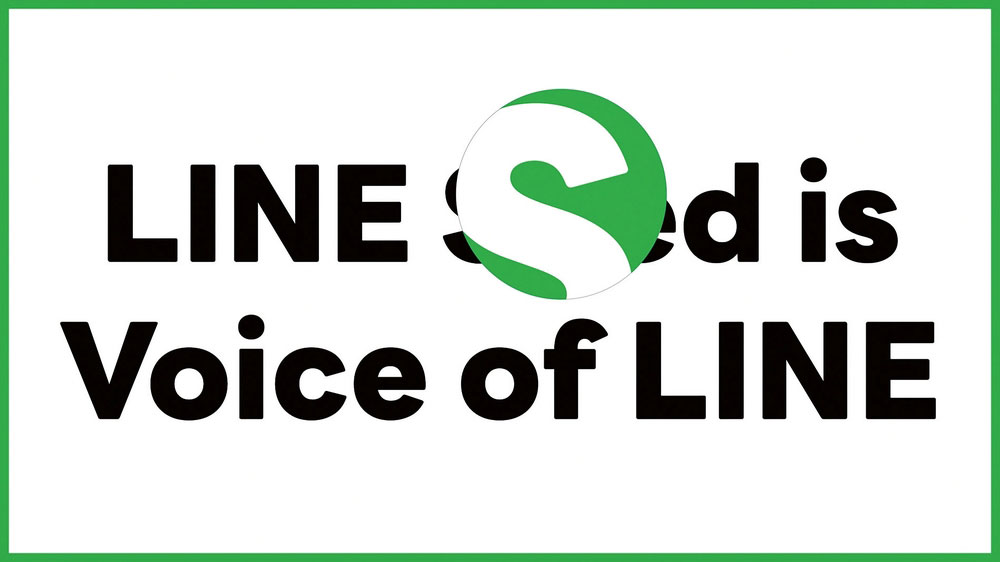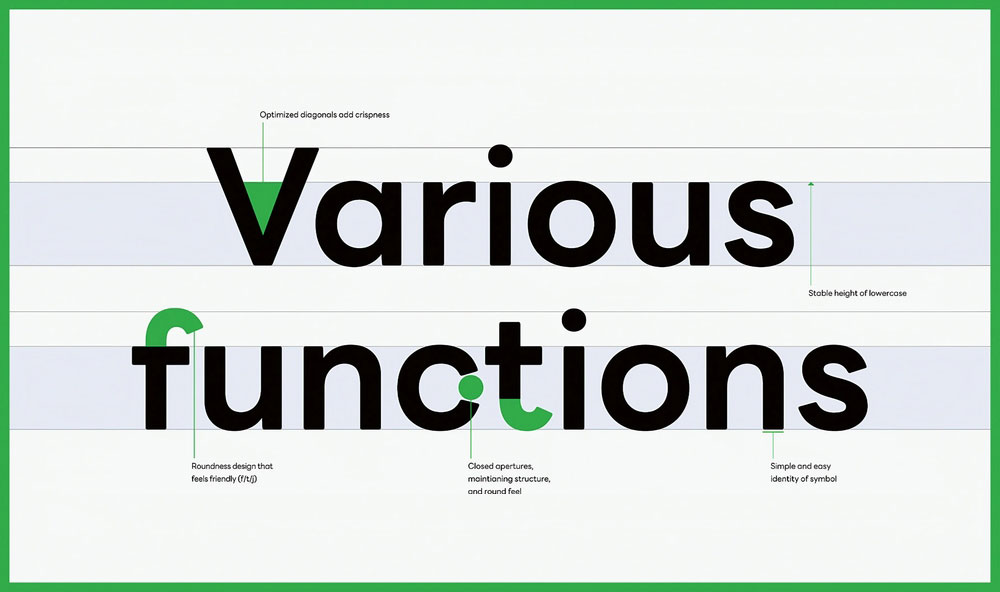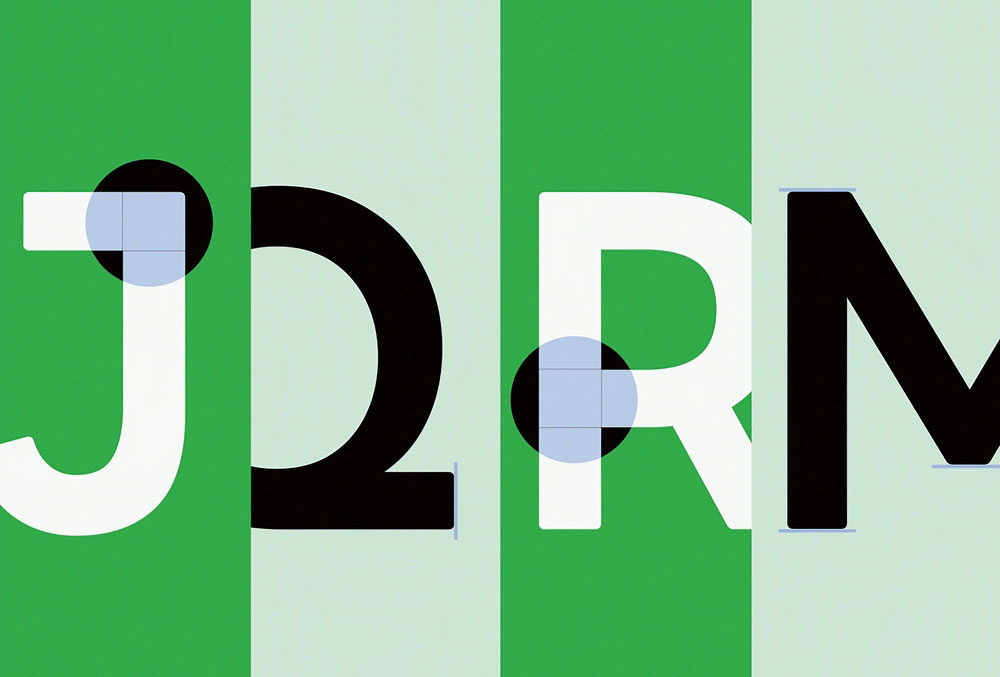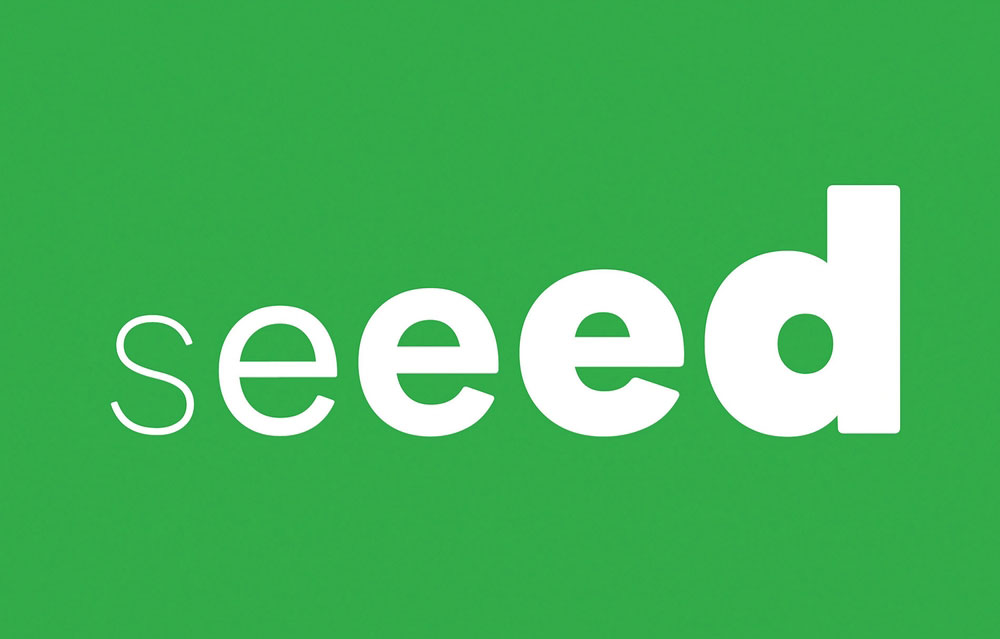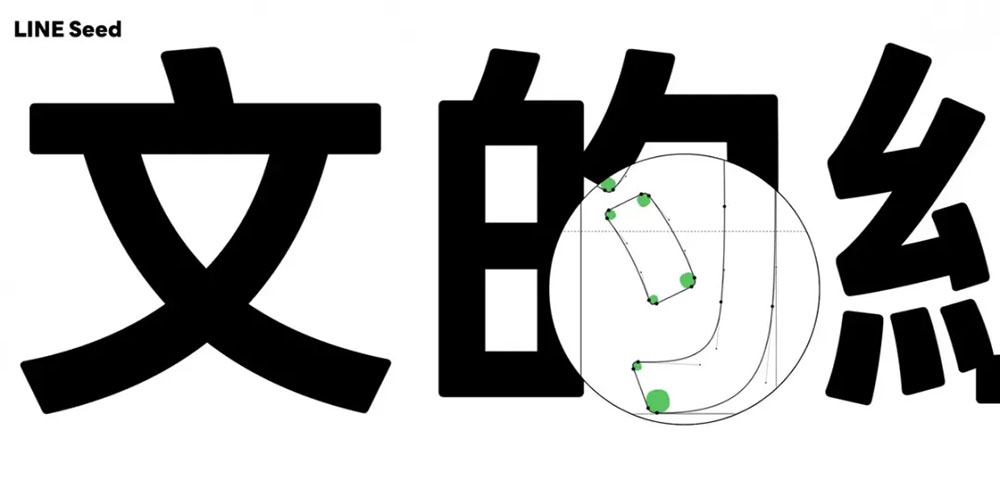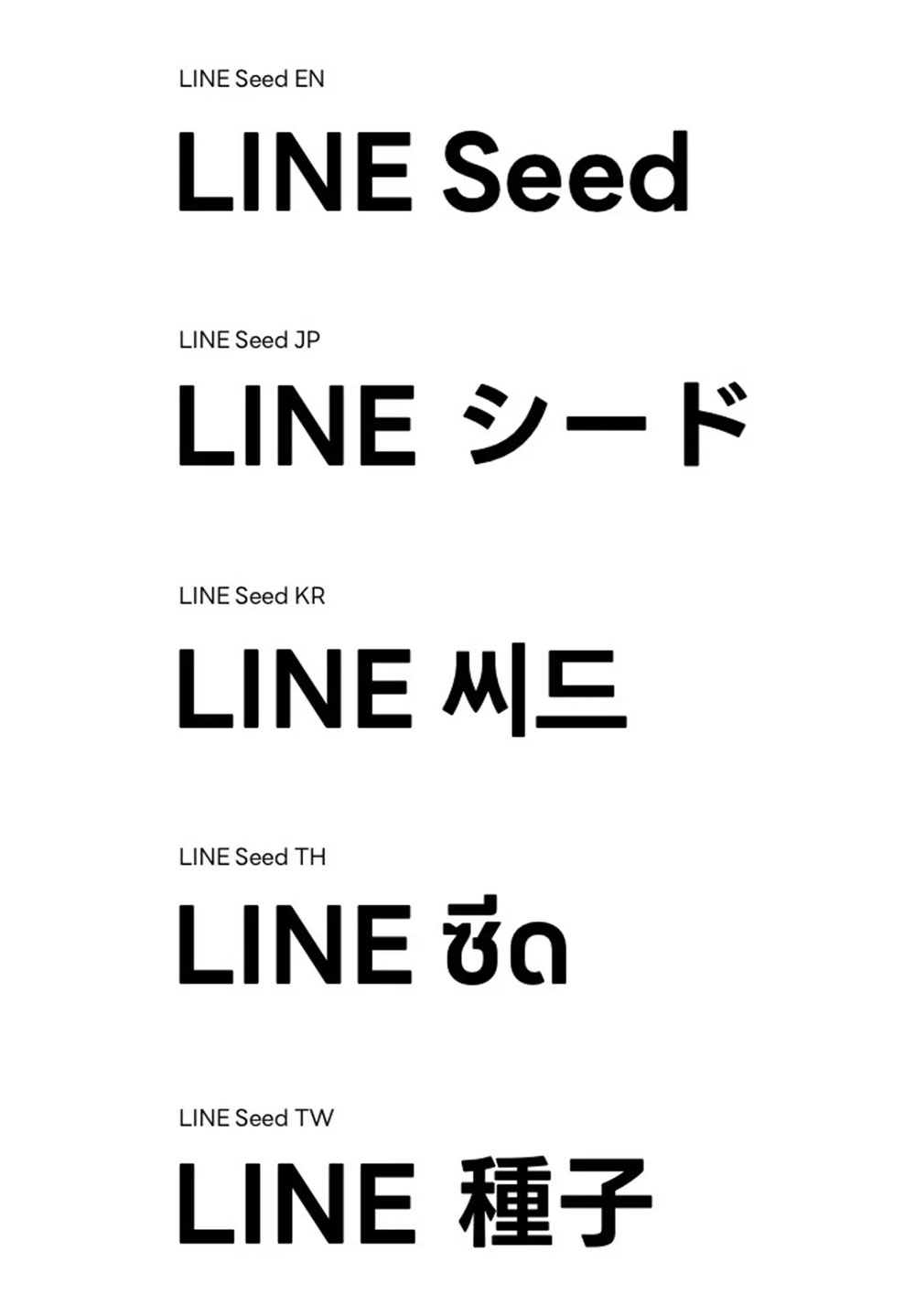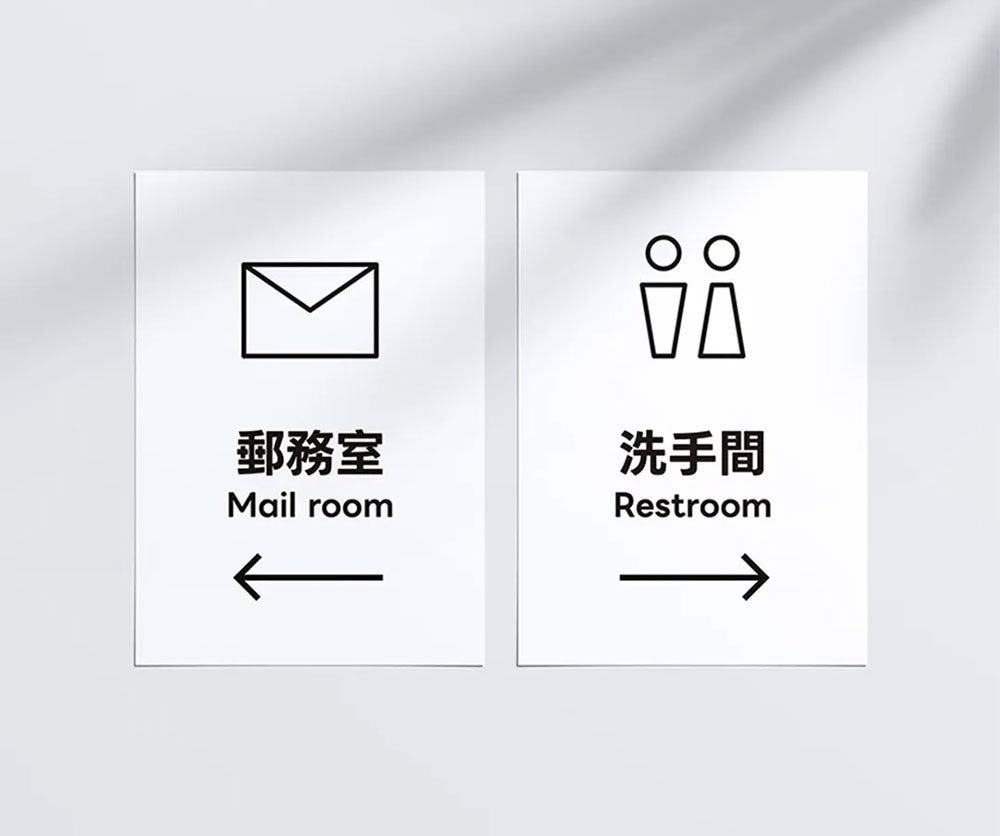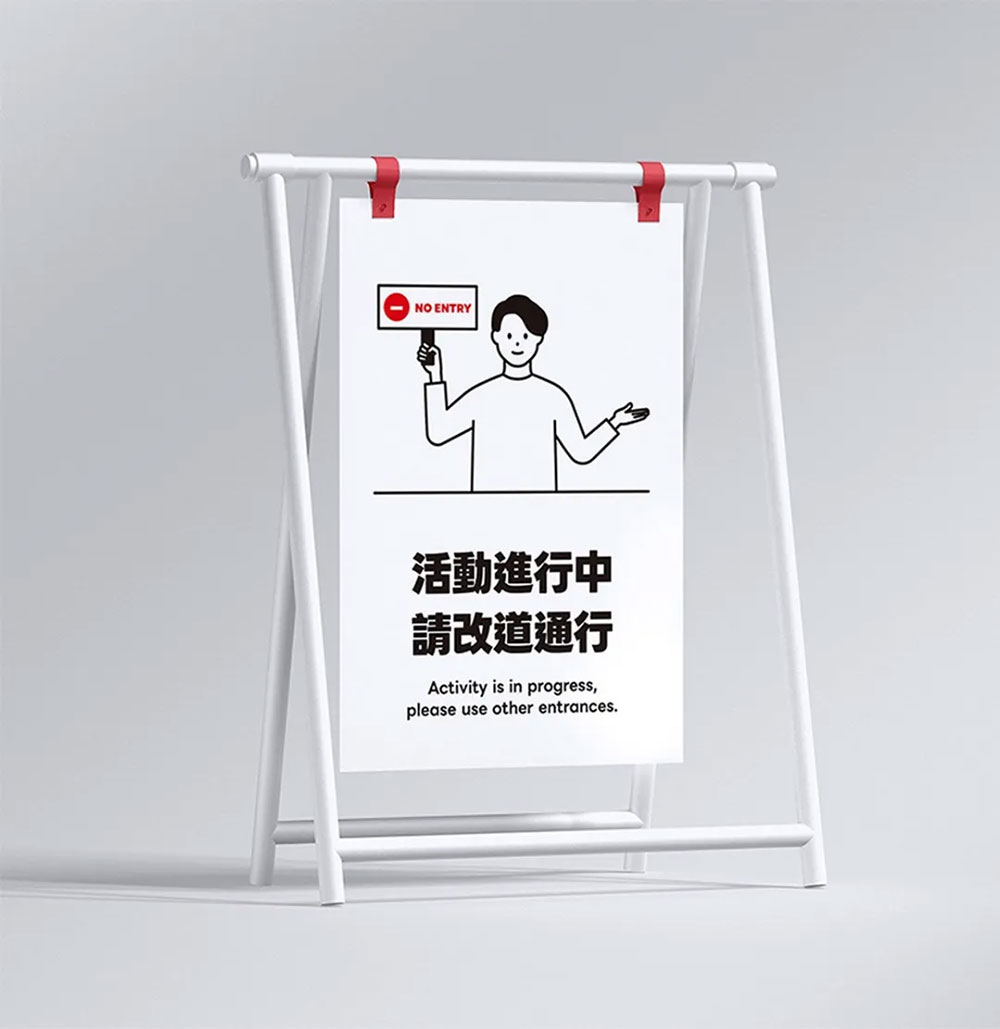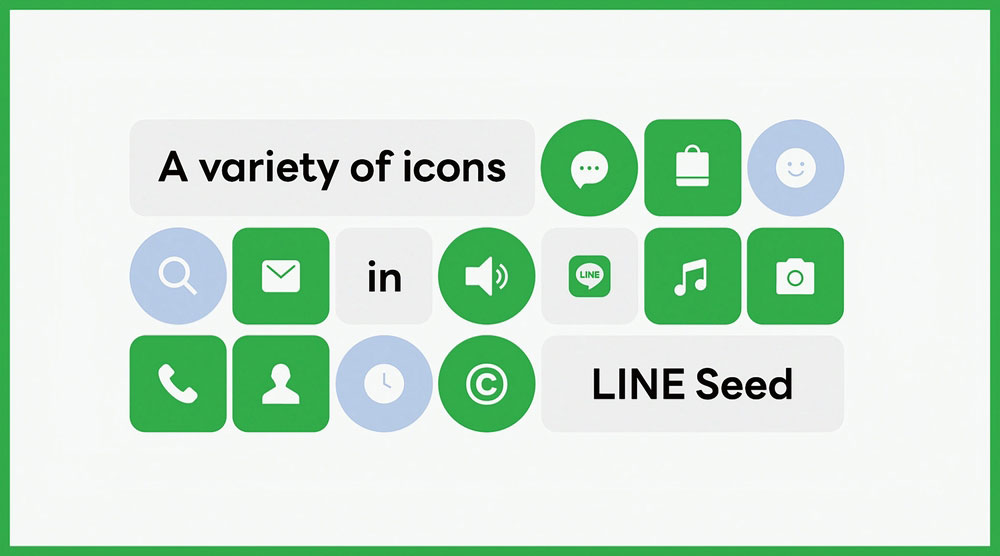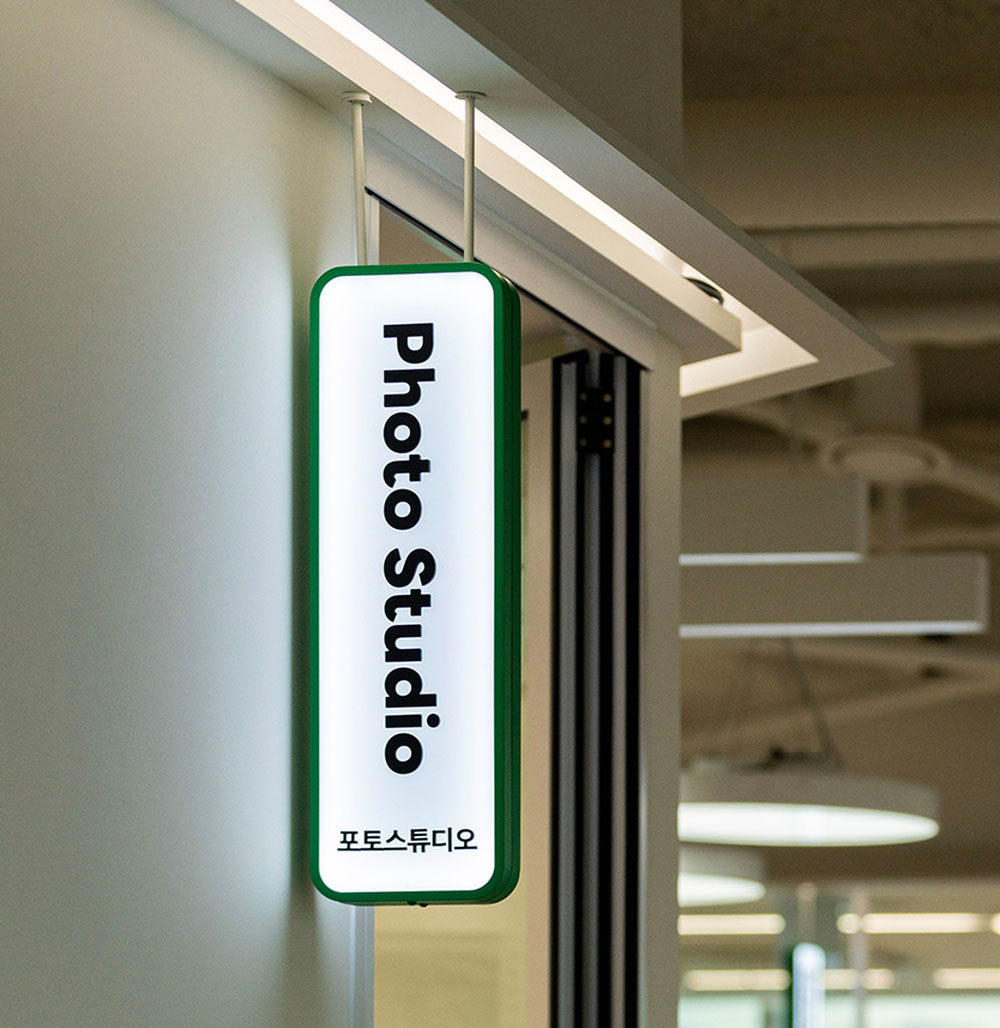
【LINE Seed】日本知名互联网公司LINE发布的品牌字体
LINE Seed 是由日本知名通讯应用公司LINE发布的一款开源免费字体,由LINE自家设计团队、中国华康字型(威锋数位)、日本Fontworks、韩国Sandoll、泰国Carson Demak、英国Dalton Maag 联合开发,覆盖繁体中文、日文、韩文、泰文、英文,主打友好、清晰、易读的设计理念,风格上中宫较大、简洁圆润、线条柔和,尤其优化了数字屏幕的显示效果,是UI和短文本的优秀选择,该字体还获得了2022年的红点设计大奖和GOOD DESIGN奖。